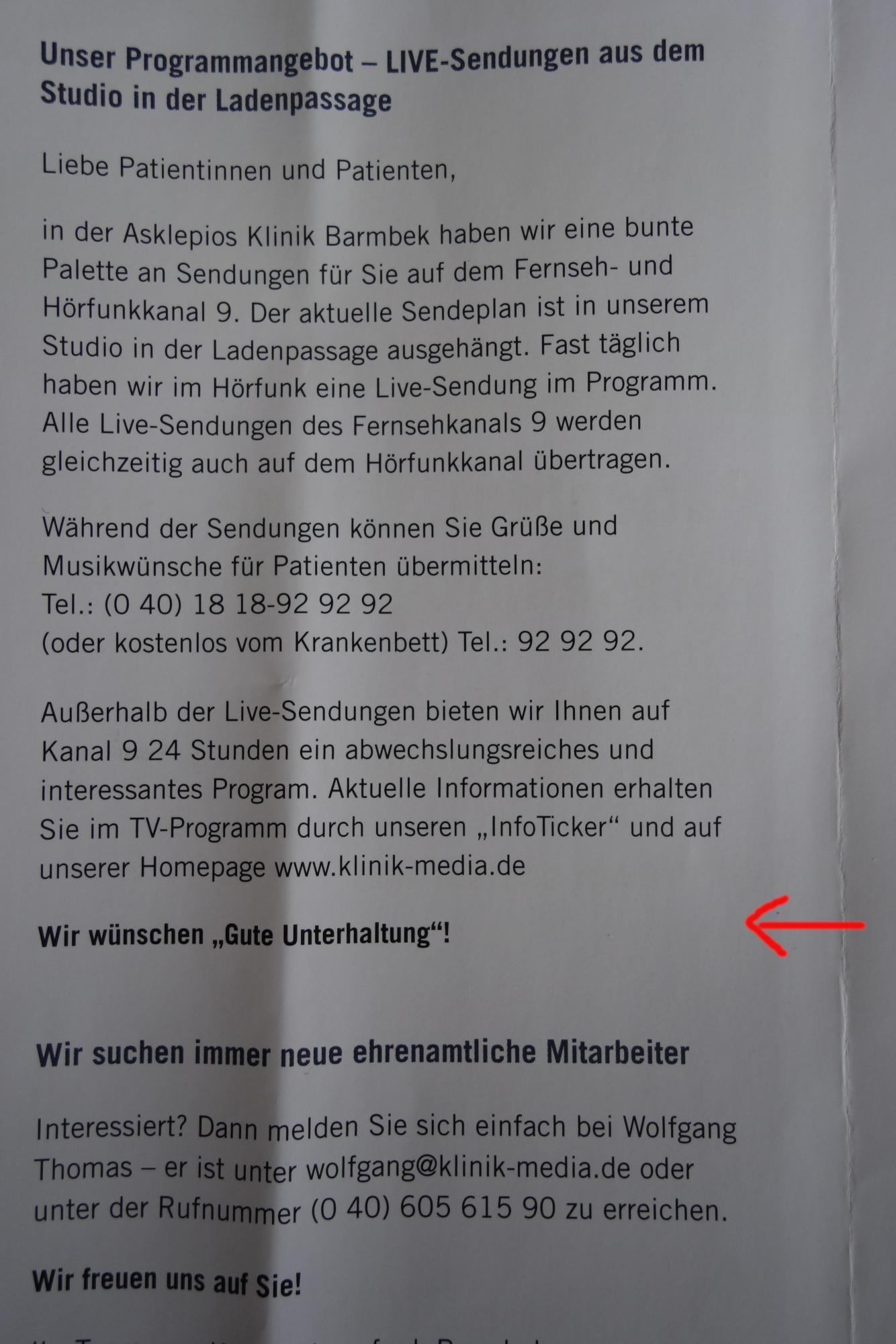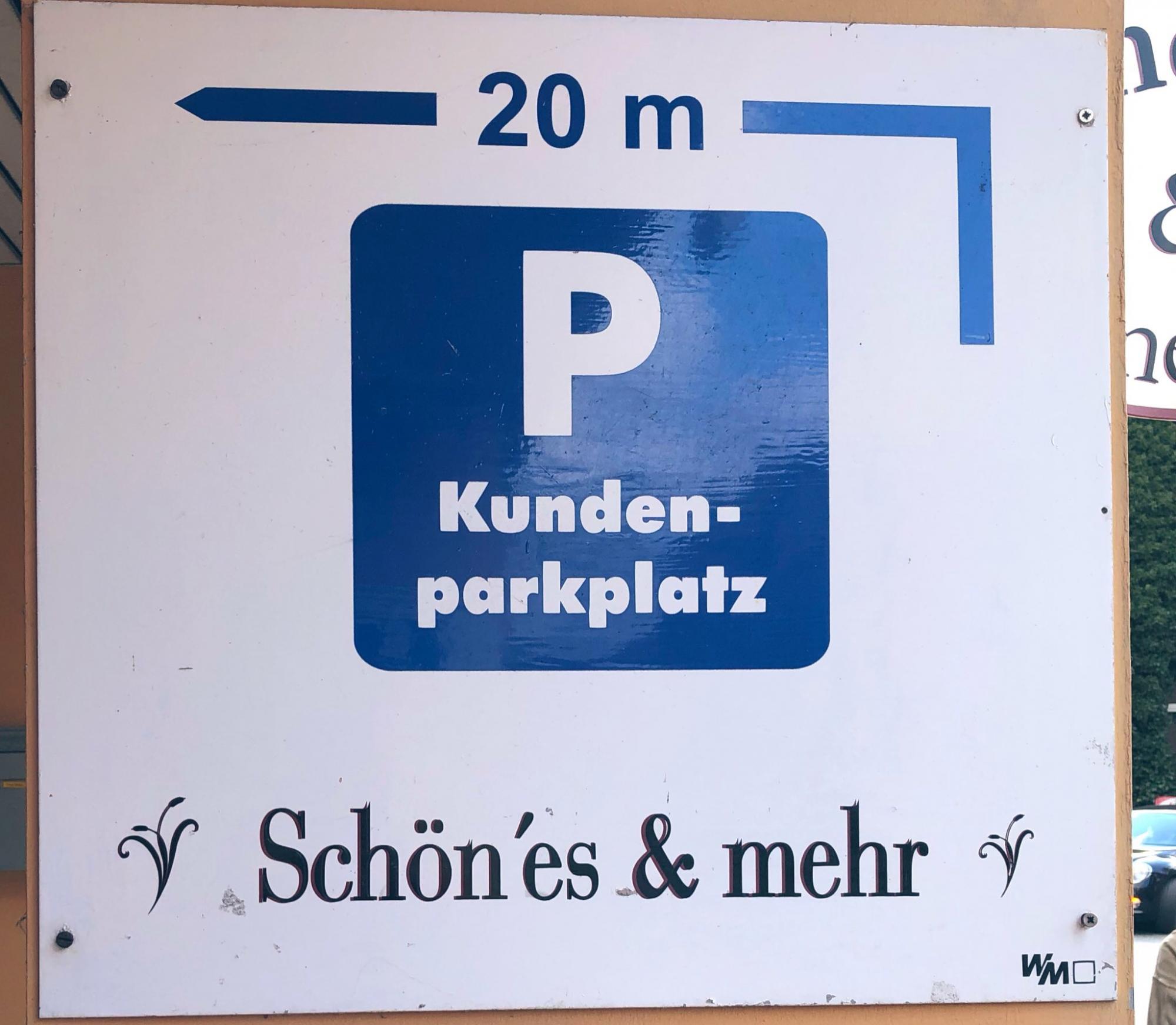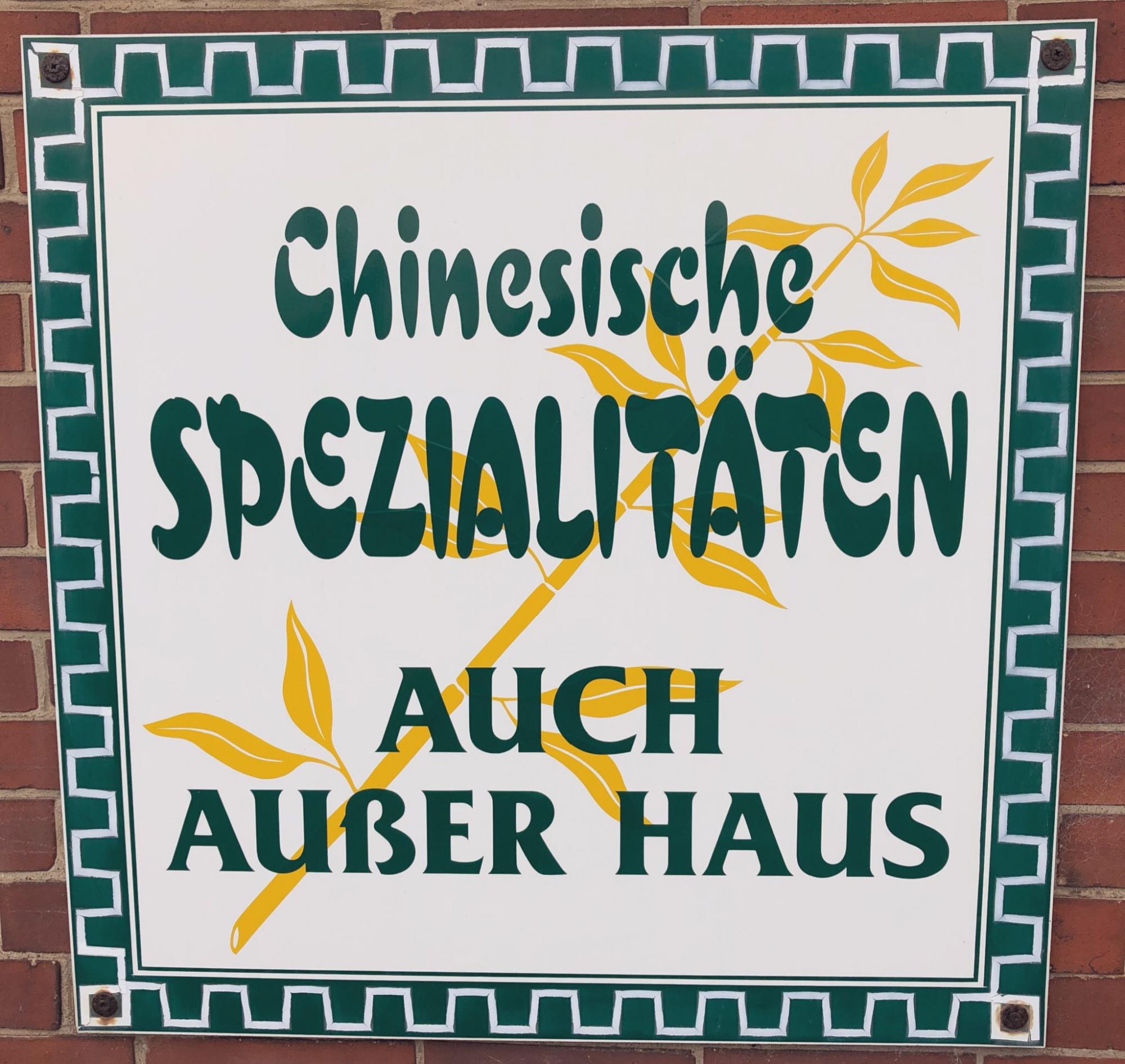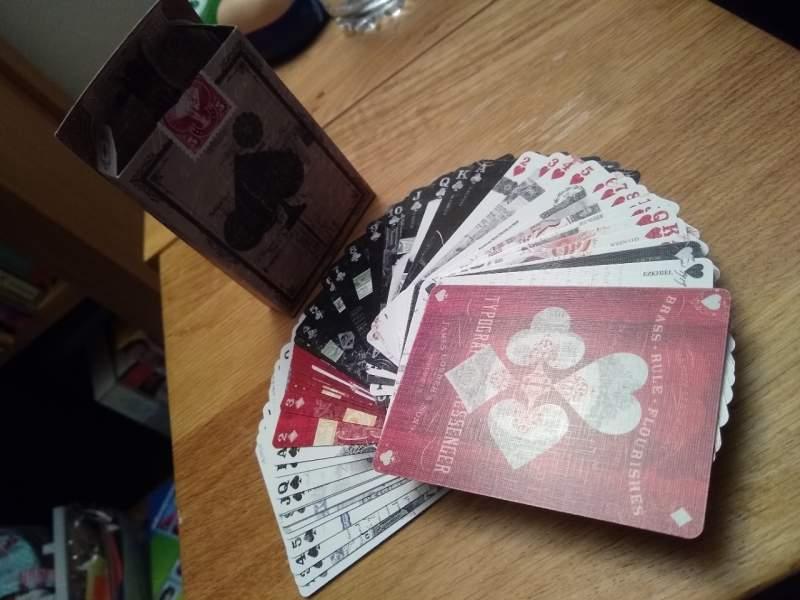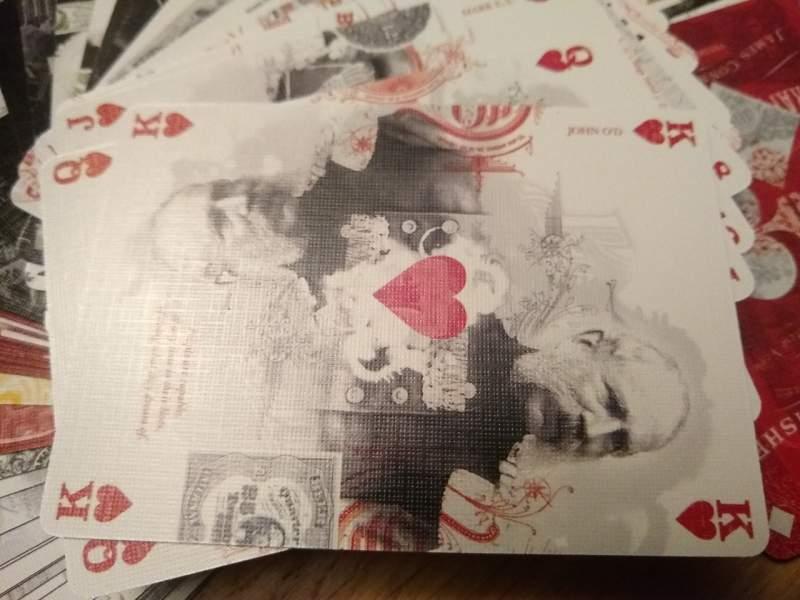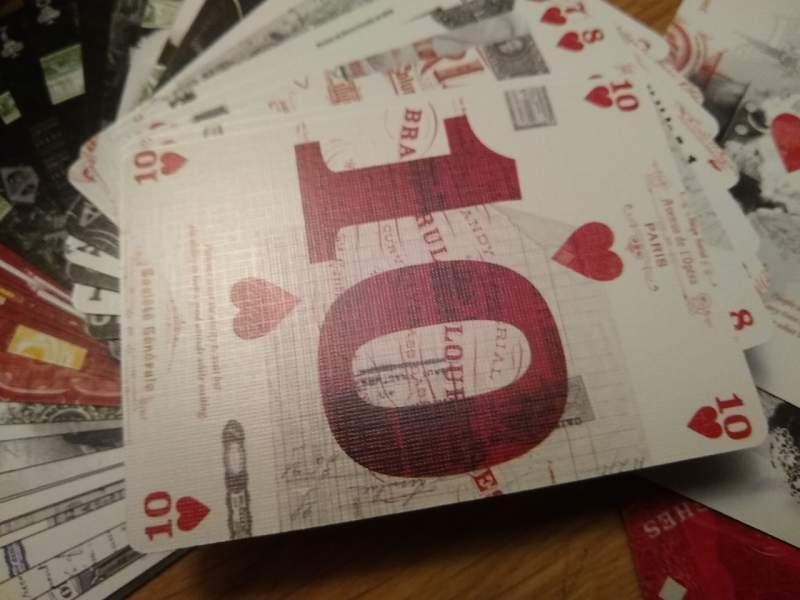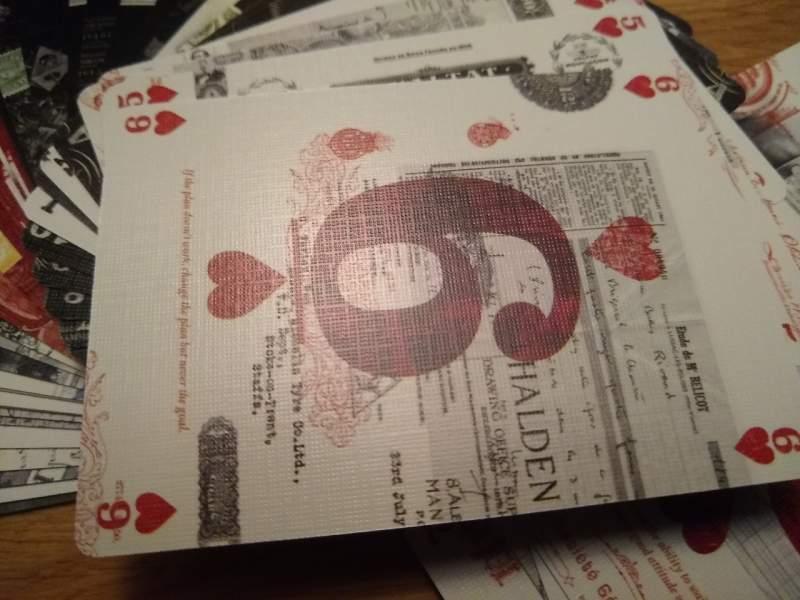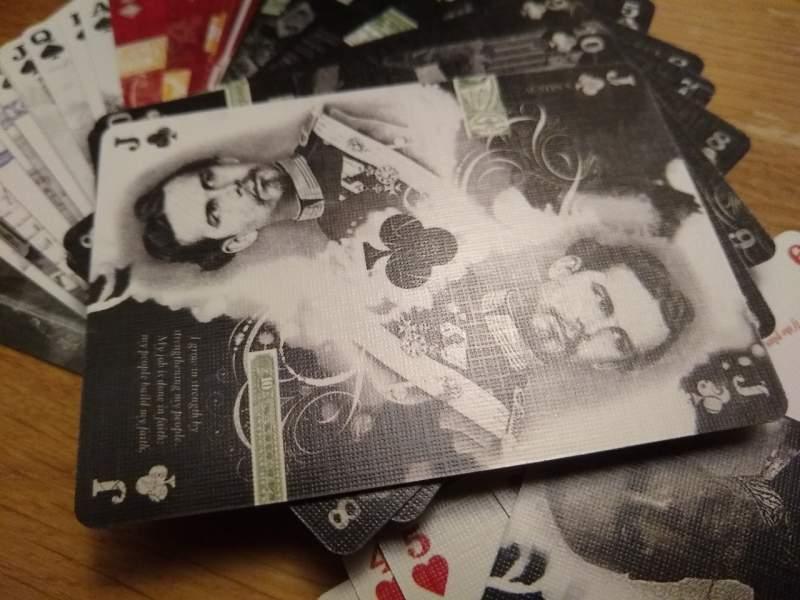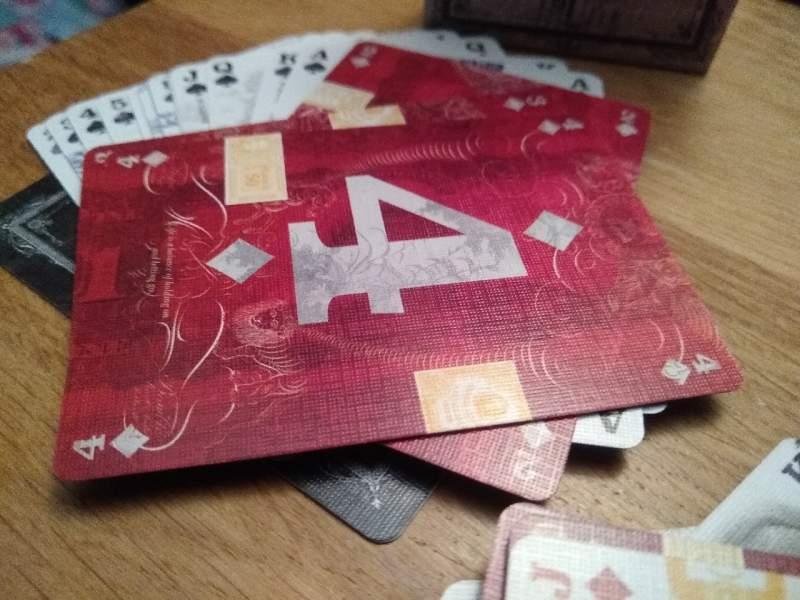
SYRIA  -  Markt
Es ist scheinbar nicht immer richtig, deutsch so zu schreiben, wie man's spricht. Ist das die Ausnahme von der Regel, die diese bestätigt,
oder  schlicht ein Lapsus?  Nun ist aber die Königsstraße auch nicht eben leicht für fremde Zungen.
Tezett in Köstritzer  und in der Schänke für k ?  Vielleicht  sollte das eigentlich eine
Schan(t)ze  werden?  Irren ist doch schließlich nur menschlich.
Ich bin jetzt nicht ganz sicher ob das hier in den Strang rein kommt .. wollte es dort einfügen wo so Wörter aufgelistet werden die durch Falschreibung etc. eine völlig andere Bedeutung bekommen.
Hier in dem sehr lesenswerten Blog hab ich doch ein köstliches Wort endeckt.
Wie jedes Jahr sind uns auch diesmal wieder die Aufzeichnungen aus den Redaktionsräumen des Schlangeneidt-Verlags zugespielt worden,
Das Flugblatt für das hausinterne Fernseh- und Radioprogramm am AK Barmbek.
Na, da sage ich „Dankeschön“!
Lange hat es gedauert, aber nun halte ich endlich die wunderschönen Ephemerid-Spielkarten von Mr Cup (Fabien Barral; Mr-CupBlog; früher Graphic Exchange) in den Händen. Die Fotos sind aus der Hüfte mit dem Mobiltelefon geschossen und daher recht grottig; vielleicht finde ich in den nächsten Tagen die Zeit noch mal anständige Aufnahmen zu machen. Einen Eindruck geben die Bilder glaube ich trotzdem. In seinem Blog finden sich weitere Informationen zu Gestaltung und Herstellung.
Ach so ...
Genau! :-)
Ich fand’s nur etwas schade, dass sie nicht konsequent die Gotham genommen haben. 🙄😅
Nicht nur cooler, sondern auch effektiver, wenn man sich die Anzahl der insgesamt benötigten bzw. der wiederholt vorkommenden Zeichen anschaut:
abcddeeeefghhijklmnoooopqrrttuuvwxyz
,aabcdefghijklmnoopqrstuuvwyxz
" the quick brown Fox..  ist m.W. so entwickelt worden, weil es darum ging, einen "stehenden Satz" als Fertigkeitsübung  für Maschinenschreiber(innen) , Tastfunker und Fernschreiber zu entwickeln.  Und da Übung erst hilft, wenn man sie häufig
genug durchführt, spielte die Anzahl der Zeichen keine Rolle. Da gilt dann wohl eher der Grundsatz: je mehr, desto besser! La.
Nicht nur cooler, sondern auch effektiver,
Effektivität müsste da genauer definiert werden: Reicht es, dass man jeden Buchstaben einmal sieht oder ist es auch interessant, mehrere Buchstabenkombinationen beurteilen (oder in der Kalligrafie üben) zu können?
Und so uncool finde ich den Fuchs gar nicht :-?
Beim Chinesen war wohl früher ein Grieche drin … :cheer:
Letzteres wohl eher nicht, wegen dem ß...
Bin ich blind? Das ist doch ein Versaleszett, oder nich?
Die Friz Quadrata hat keines, das gezeigte ist ein kleines ß.
Beim Chinesen war wohl früher ein Grieche drin … :cheer:
Oder der Grieche bietet jetzt China-Essen an, so wie ich viele arabische Pizzabäcker erlebt habe.
Der China-Mann ist schnell und günstig und dafür gar nicht schlecht – der Grieche vor Ort vice versa.
Der verkorkste Apostroph rührt wohl daher, dass der Ladeneigentümer Schön heißt – natürlich hätte man trotzdem ein echtes Apostroph nehmen können …
War beides wohl (laaange) vor meiner Zeit, aber die Schnitzelisierung Otterndorfs schreitet voran :hammer:
Beim Chinesen war wohl früher ein Grieche drin … :cheer:
Nunja, nur weil der olle Mäanderfluss in Griechelnad zu liegen kam, heißt das ja noch lange  nicht, dass die das Muster auch erfunden haben ...
nur weil der olle Mäanderfluss in Griechelnad zu liegen kam,
Ich glaub, die Türken haben da eine andere Meinung zu... :D
Und ein Vertreter eines zweihäusigen Schriftsystems ist halt immer dann »außer Haus«, wenn er sich (vermeintlich oder tatsächlich) im falschen »Haus« tummelt. Also irgendwie passt das schon alles. ;-)